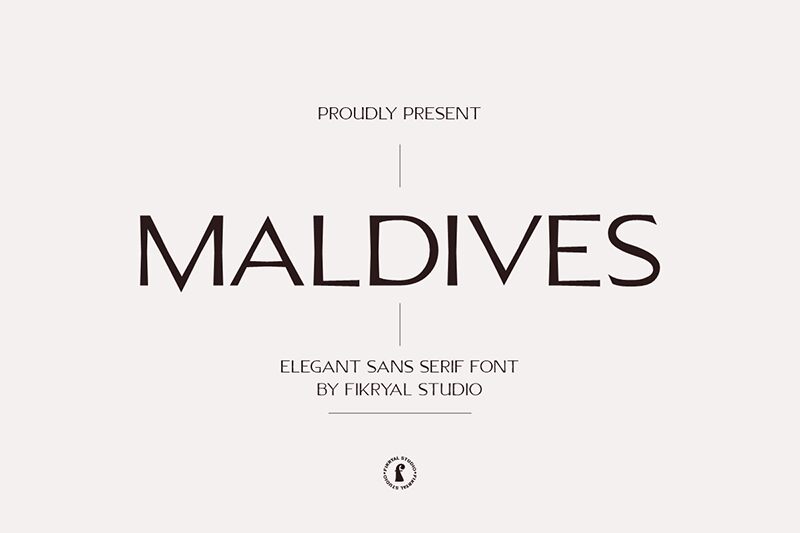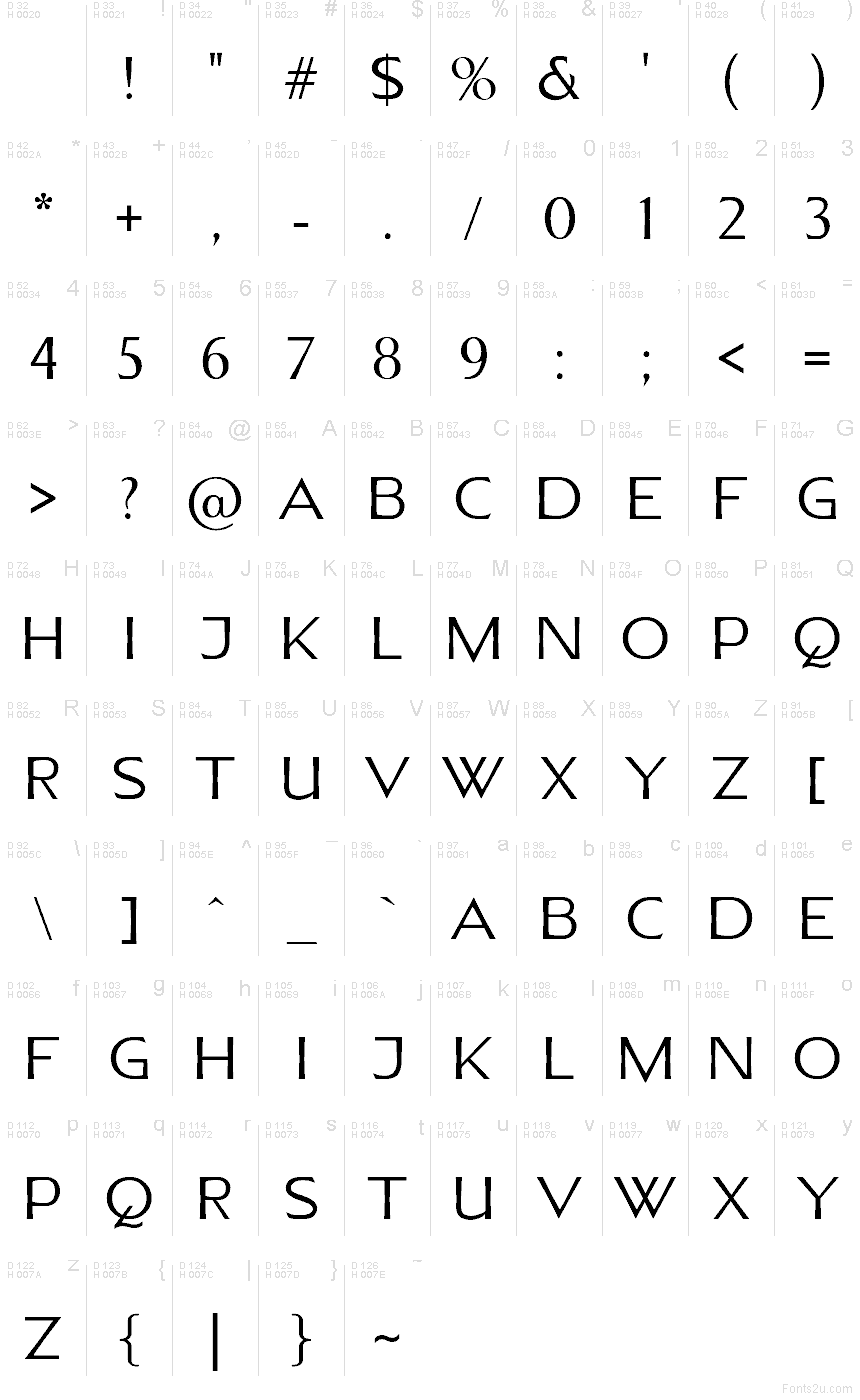
Die Schriftart Maldives Sans von Muhamad Fikry Nuralif (Fikryal Studio) ist eine kostenlose serifenlose Schrift mit einem hauchdünnen, luftigen Look, der an feine, mit einem einzigen Draht gezogene Linien erinnert. Die hohen Großbuchstaben und das großzügige Laufweiten-Design verleihen Wörtern einen ruhigen, gehobenen Rhythmus, während scharfe Winkel für eine klare, moderne Ästhetik sorgen, ohne dabei zu zerbrechlich zu wirken.
Mit Maldives Sans setzen Sie klare Akzente bei Magazin-Titelzeilen, Beauty-Verpackungen, Tech-Branding, minimalistischen Plakaten, Album-Covern, Hero-Texten auf Websites oder bei der Beschilderung von Boutiquen. Diese kostenlose Schrift kommt am besten zur Geltung, wenn sie Raum zum Atmen hat – probieren Sie größere Schriftgrade und zusätzliches Letterspacing aus. Kombinieren Sie sie für den Fließtext mit einer warmen, gut lesbaren Serifenschrift oder einem robusten Neo-Grotesk.